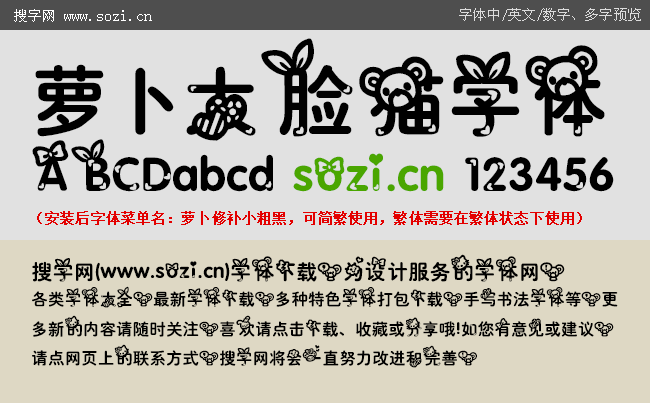
蘿卜大臉貓字體
搜字網(wǎng)給大家提供一款很可愛的手機(jī)中文字體下載。字體名叫蘿卜大臉貓字體,這款手機(jī)字體是以圓體字體為原形,筆畫間插入了可愛的卡通圖案。在具備圓字體清晰端正的風(fēng)格同時(shí),卡通味也特別濃,是一款非常可愛的卡通字體,特別適合喜歡手機(jī)字體個(gè)性一些的朋友在手機(jī)上安裝使用。